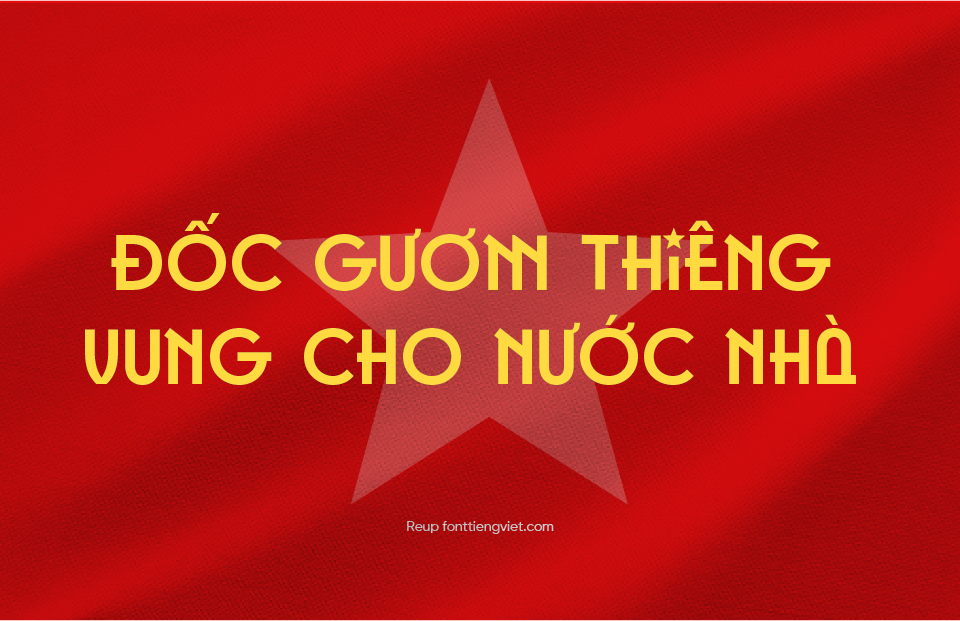
Font tiếng Việt Patriot
Giới thiệu về Font tiếng Việt Patriot
Trong thế giới đồ họa hiện đại, việc tìm kiếm một bộ Font Miễn Phí chất lượng cao luôn là ưu tiên hàng đầu của các nhà thiết kế và học sinh sinh viên. Font tiếng Việt Patriot nổi lên như một lựa chọn hoàn hảo nhờ phong cách mạnh mẽ, hiện đại và đầy cá tính. Đây là bộ font chữ được tinh chỉnh kỹ lưỡng để phù hợp với bảng mã tiếng Việt, giúp người dùng không còn lo lắng về lỗi hiển thị dấu khi soạn thảo văn bản hay thiết kế ấn phẩm truyền thông chuyên nghiệp.
Tại sao nên chọn Font tiếng Việt Patriot cho dự án?
Đặc điểm nổi bật của bộ font này chính là những đường nét dứt khoát, mang lại cảm giác tin cậy và tinh thần yêu nước đúng như tên gọi của nó. Font tiếng Việt Patriot rất phù hợp để sử dụng trong các bài thuyết trình tại nhà trường, thiết kế áo đồng phục hoặc làm tiêu đề cho các video sáng tạo trên mạng xã hội. Sự linh hoạt giữa các nét dày và mỏng tạo nên một nhịp điệu thị giác ấn tượng, giúp nội dung của bạn dễ dàng thu hút sự chú ý của người xem ngay từ cái nhìn đầu tiên.
Lưu ý khi sử dụng trong học tập và thiết kế
Mặc dù đây là một bộ font chữ đẹp, bạn nên kết hợp Font tiếng Việt Patriot với các font không chân tối giản khác để tạo sự cân bằng cho bố cục. Việc sử dụng font này cho các tiêu đề lớn sẽ đạt hiệu quả thẩm mỹ cao nhất. Hy vọng bộ Font Miễn Phí, Font Việt Hóa, Font tiếng Việt Patriot này sẽ trở thành công cụ đắc lực, giúp bạn hoàn thành những sản phẩm thiết kế xuất sắc và đầy ý nghĩa trong tương lai.